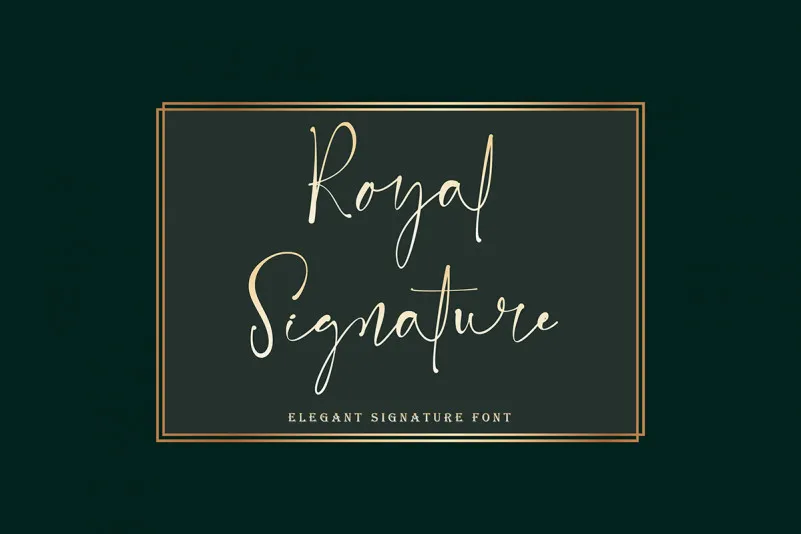
Royal Signature Font – Download Grátis
Esta é uma elegante fonte de traço feito à mão, perfeita para escrita manuscrita. A Royal Signature Font apresenta duas opções de estilo: regular e itálico. Equipada com uma qualidade excepcional, a fonte transmite uma sensação natural e sofisticada que se destaca em qualquer trabalho. Ideal para todas as aplicações, desde o design de convites casamento, cartões de negócios, logotipos comerciais, atualizações nas mídias sociais, citações, marcação, decorações, até banners com os diversos tipos de negócio que você possa ter. A Royal Signature Font é uma fonte perfeita para personalizar seu trabalho e expressar sua identidade visual de maneira única.